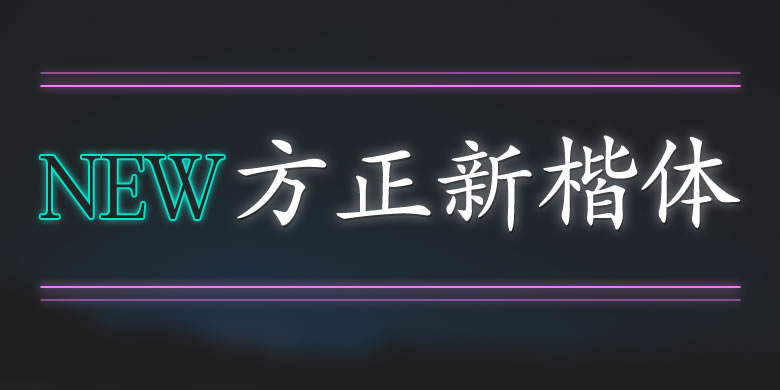
方正新楷体
方正新楷体是方正楷体的深度优化版。方正楷体制作年代较早,复刻自铅字楷体字稿,限于当时的技术手段,细节不够完善。方正新楷体的笔法更为讲究,笔画分明利落,字形端正,细节精致,曲线节点的位置都有明确规则。相对原方正楷体,方正新楷体的字面稍大,中宫也稍放松,文本灰度均匀统一,是一款优良的正文排版字体。